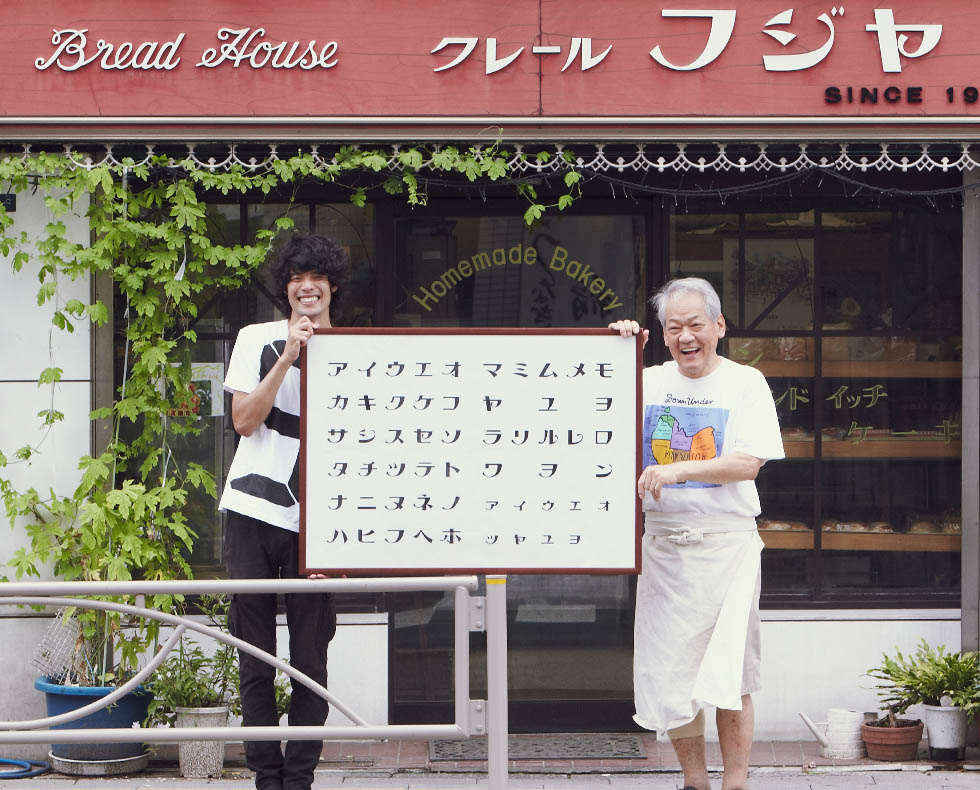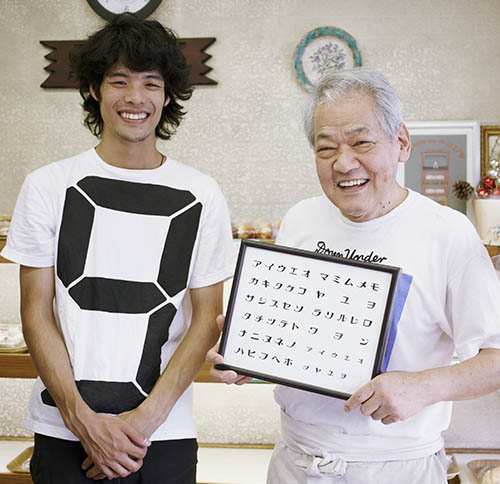
遠い昔、夏休みに祖母の家で出されたお菓子の包みを思い出す。この書体は懐かしきエレガントさに満ちあふれている。郷愁を誘う優美な雰囲気を湛えた書体。
「クレールフジヤ」は看板にもある通りの1932年に開業したパン屋さん。現店長の白石さんは今年で74才。二代目だ。現在は白石さんひとりでパンを焼き、配達、経営もしている。現在のお店には1955年に製造拠点を移したそうだ。店構えは西洋を感じさせる。看板の書体はこの外観に合わせて知り合いの建築会社がデザインしたという。「おれがドイツ行ったのね、洋菓子の研修で。約一ヶ月近くかな。ヨーロッパで。そのときに材木で組んであるような木組みの中世の町に洋菓子学校があって。それが印象に残ってる。だけど、それを(建築会社に)話したかどうかってのがわかんないんだけど…。まぁ、うまくそれに合致したんだな、ははは」と白石さんは語る。小さなパン屋さんにピッタリのかわいい書体だ。
As the sign says, “Claire Fujiya” is a bakery that opened in 1932. The current manager, Mr. Shiraishi, is 74 years old this year. He is the second generation. Currently, Mr. Shiraishi bakes, delivers, and manages the bakery by himself. He moved the production base to the current store in 1955. The store’s appearance has a Western atmosphere. The typeface of the signboard was designed by an architectural firm that he knows. “I went to Germany for training to make confectionery. I was in Europe for about a month. There was a confectionery school in a medieval town with a wooden structure made of lumber. That left an impression on me. But I don’t know if I told the architectural firm about it or not... Well, it may have seemed that it fits nicely, haha.” Mr. Shiraishi said. It’s a cute typeface, perfect for a small bakery.